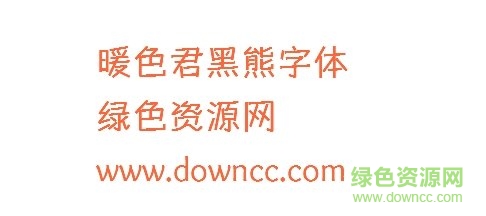
暖色君黑熊字體是一款干凈簡潔藝術(shù)字體,端正中帶點(diǎn)彎曲,給字跡流動(dòng)張揚(yáng)的美,有著極佳的視覺呈現(xiàn),綠色資源網(wǎng)等你現(xiàn)在收藏!
暖色君黑小熊是新浪微博暖色君分享的手寫字體,無論中文漢字還是英文字母都有著不錯(cuò)的藝術(shù)構(gòu)造,字體連貫二統(tǒng)一,書寫效果不錯(cuò),可以廣泛運(yùn)用于logo設(shè)計(jì)、文字排版、海報(bào)創(chuàng)意等諸多領(lǐng)域!